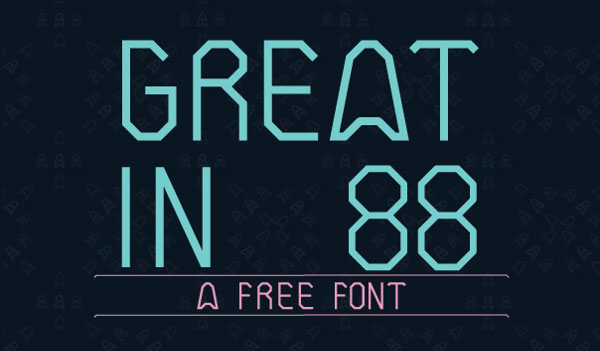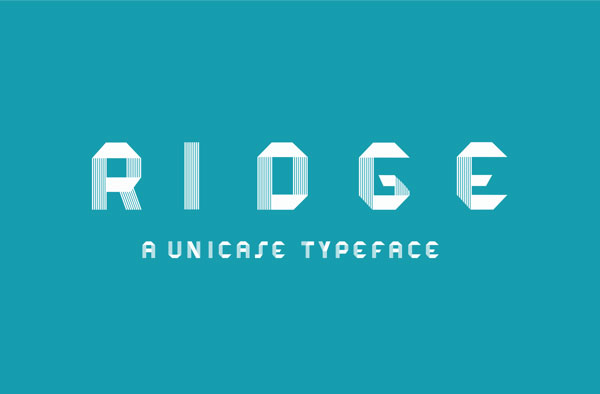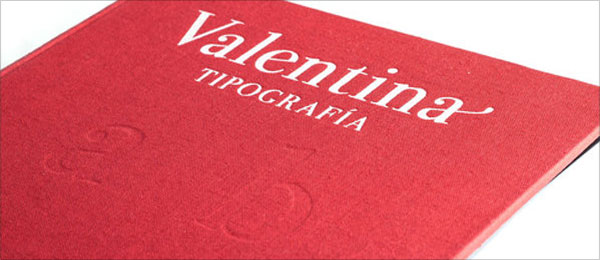
15个风格较华丽的英文字体
收集了一些 Gorgeous 即华丽风格的字体,可用于一些比较常见的图像处理中,例如标题、海报等大型文字作品。
RIDGE Free Typeface for Typography
AVENTURA Free Bold font for Packaging 2015
Oranienbaum Perfect Modern free font for logo design
Lovinn Free Font
Valentina Perfect Stylish sans serif typeface
Great In 88 Free Font Family for tech related design projects
Kontanter Free Font
Elcsa Font
One Day Free Font
Growl Free Font
Erster Caps Free Font
Fabfelt Script
Free Liberal Hand Serif Font
Bellaboo – Free Hipster Font
Harlott Free Font
Lovinn Free Font